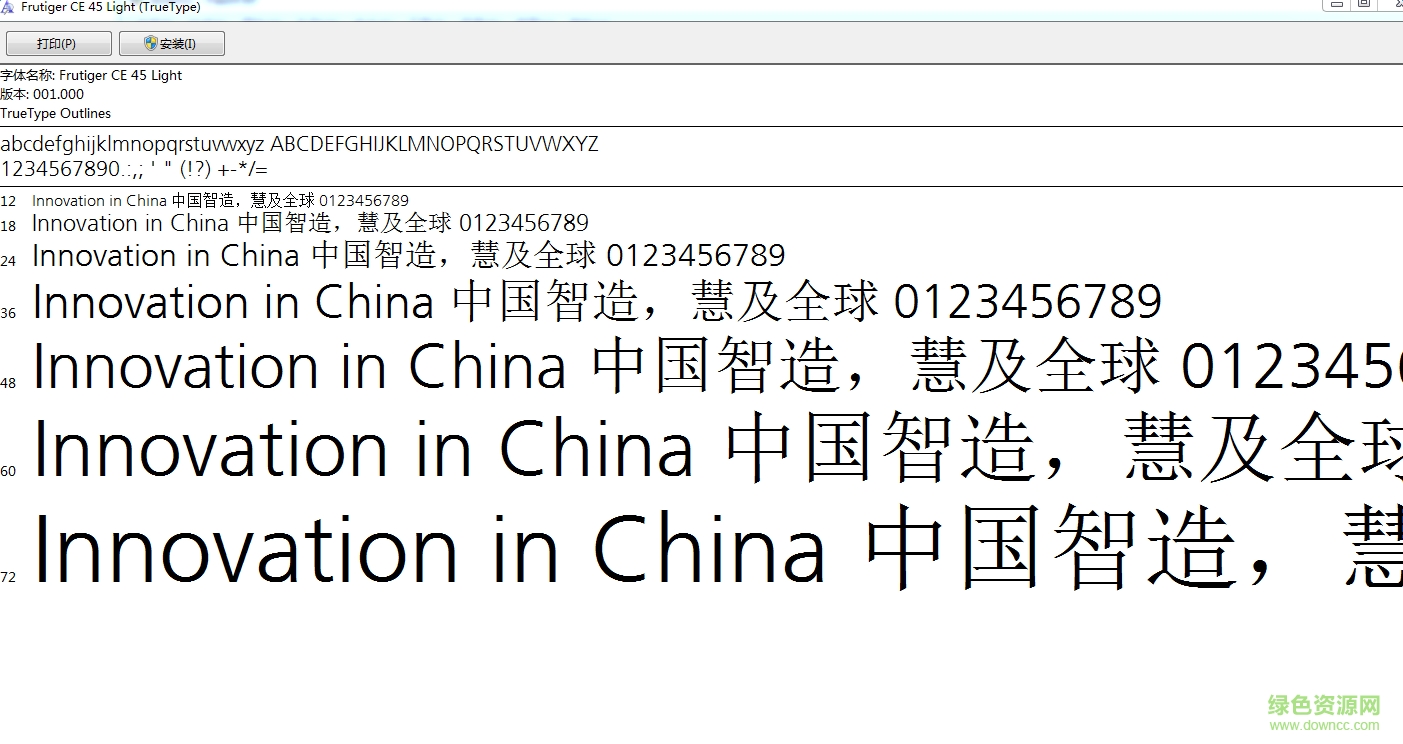
frutiger light字體是一款無襯線英文字體,字形工整,結(jié)構(gòu)得當(dāng),易讀性較強,可應(yīng)用于廣告、路標(biāo)、印刷、報刊等各個領(lǐng)域,歡迎大家前來下載!
frutiger light字體線條流暢,細節(jié)出色,整體整潔美觀,看上十分休閑,需要的朋友快來綠色資源網(wǎng)下載吧!